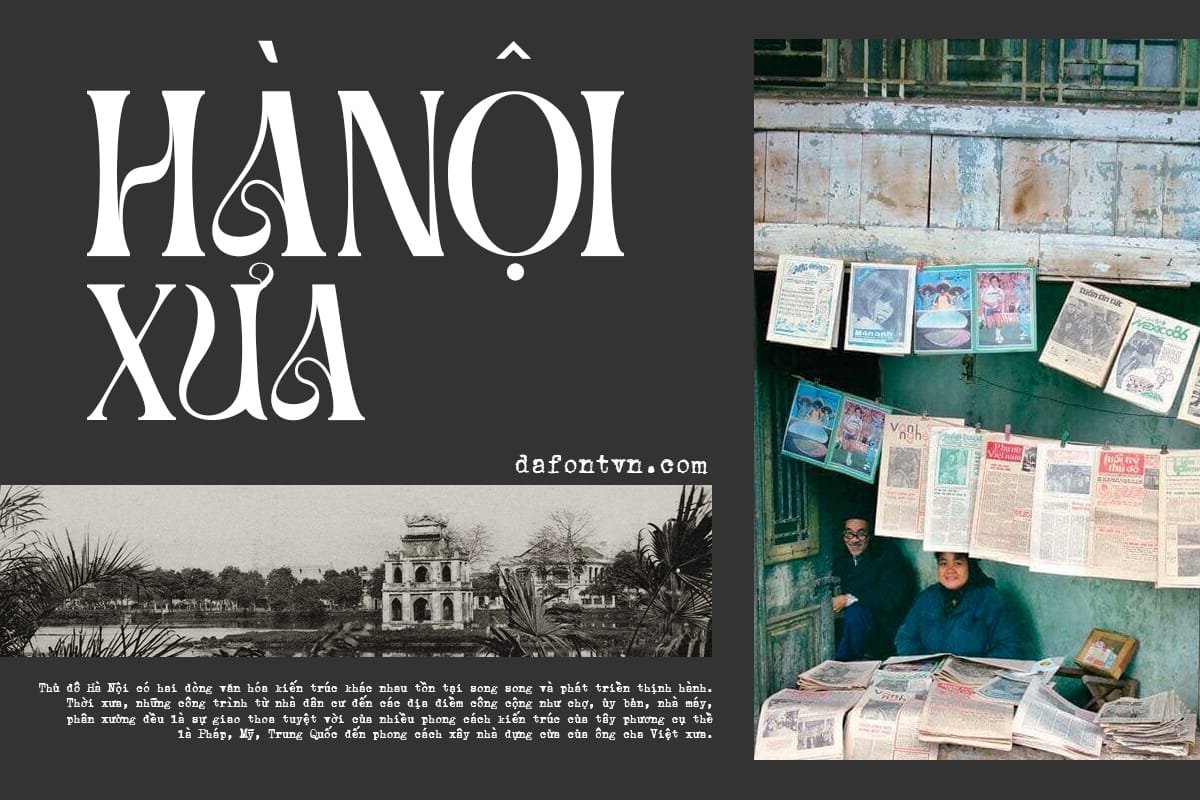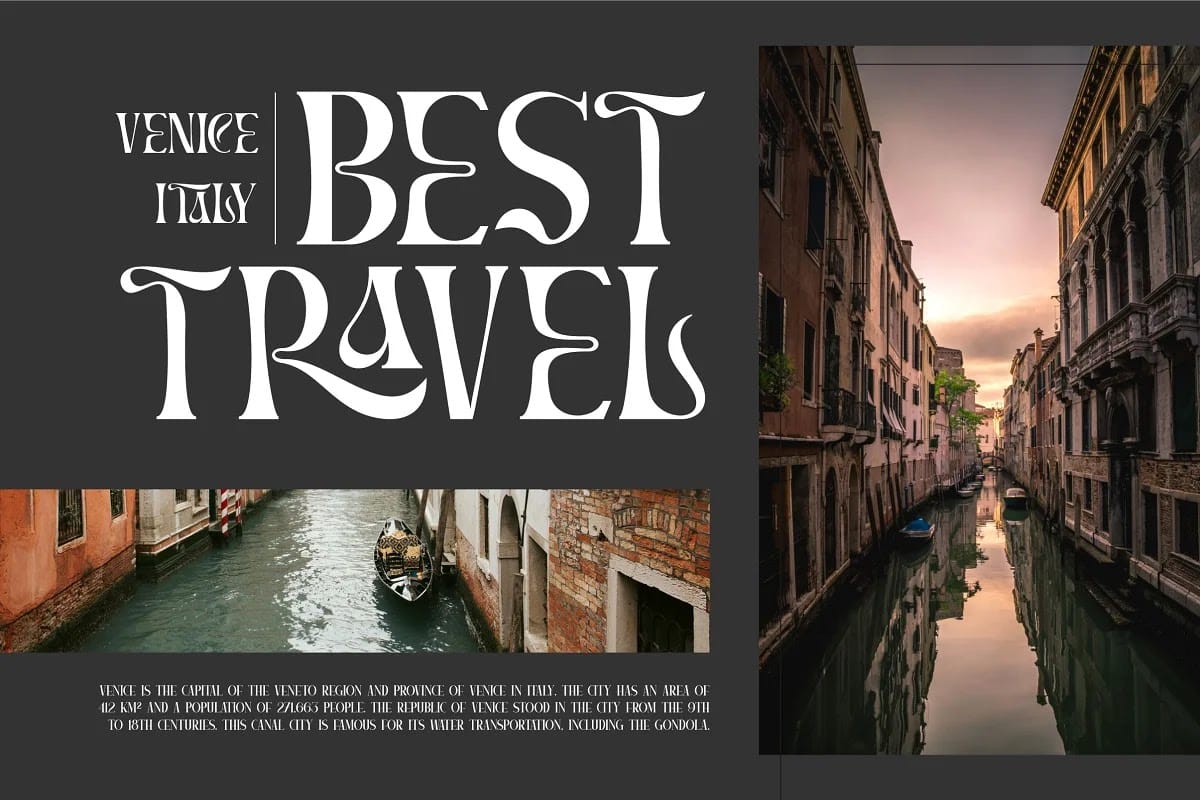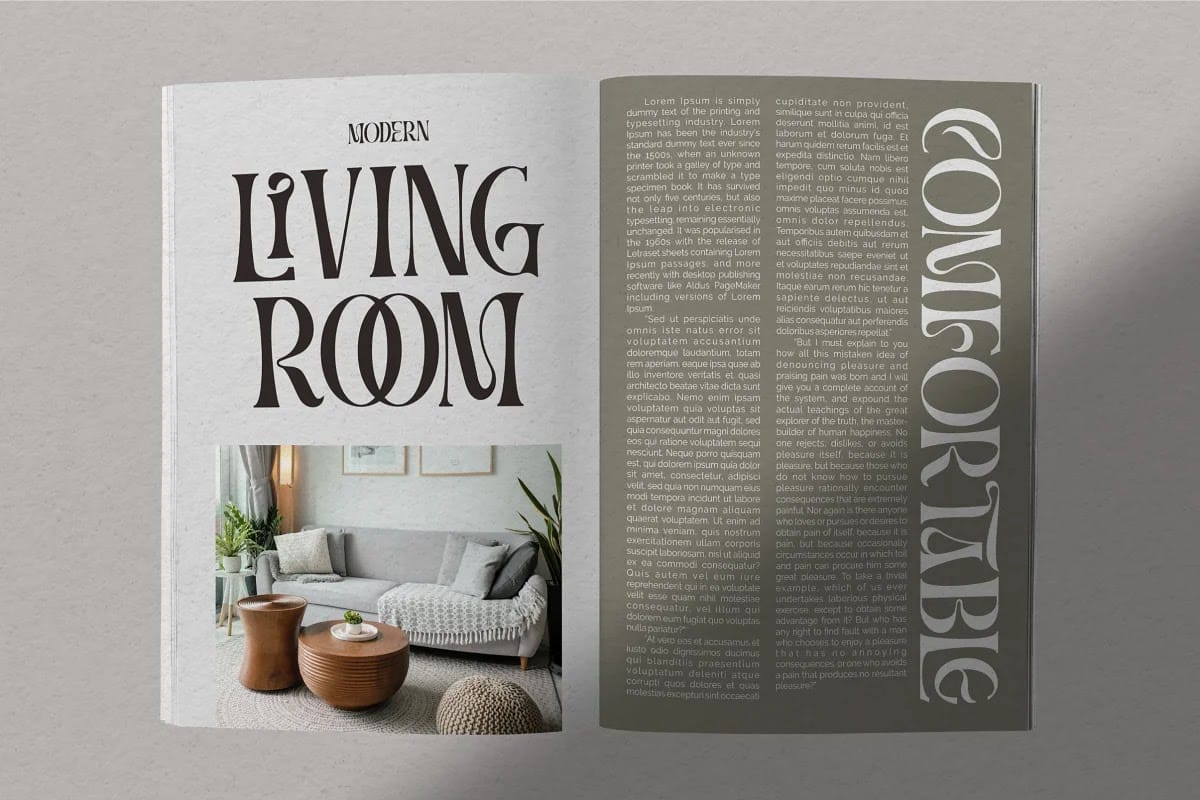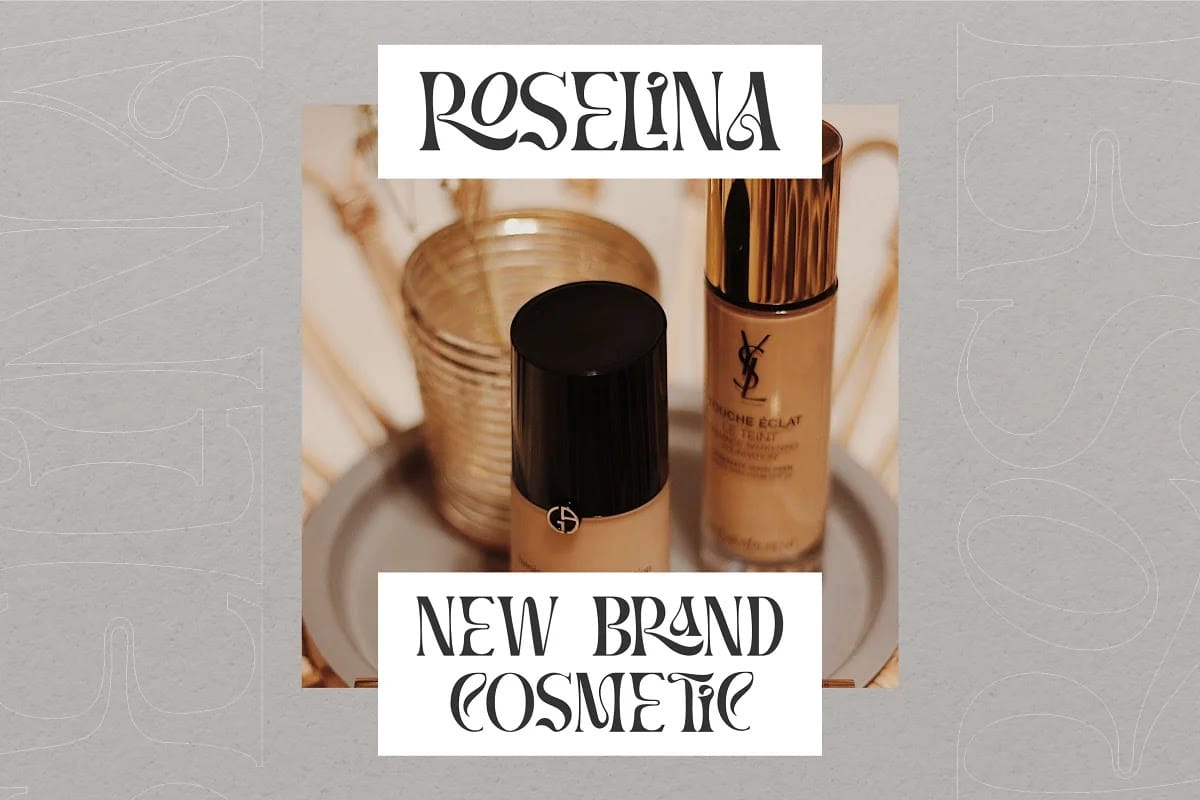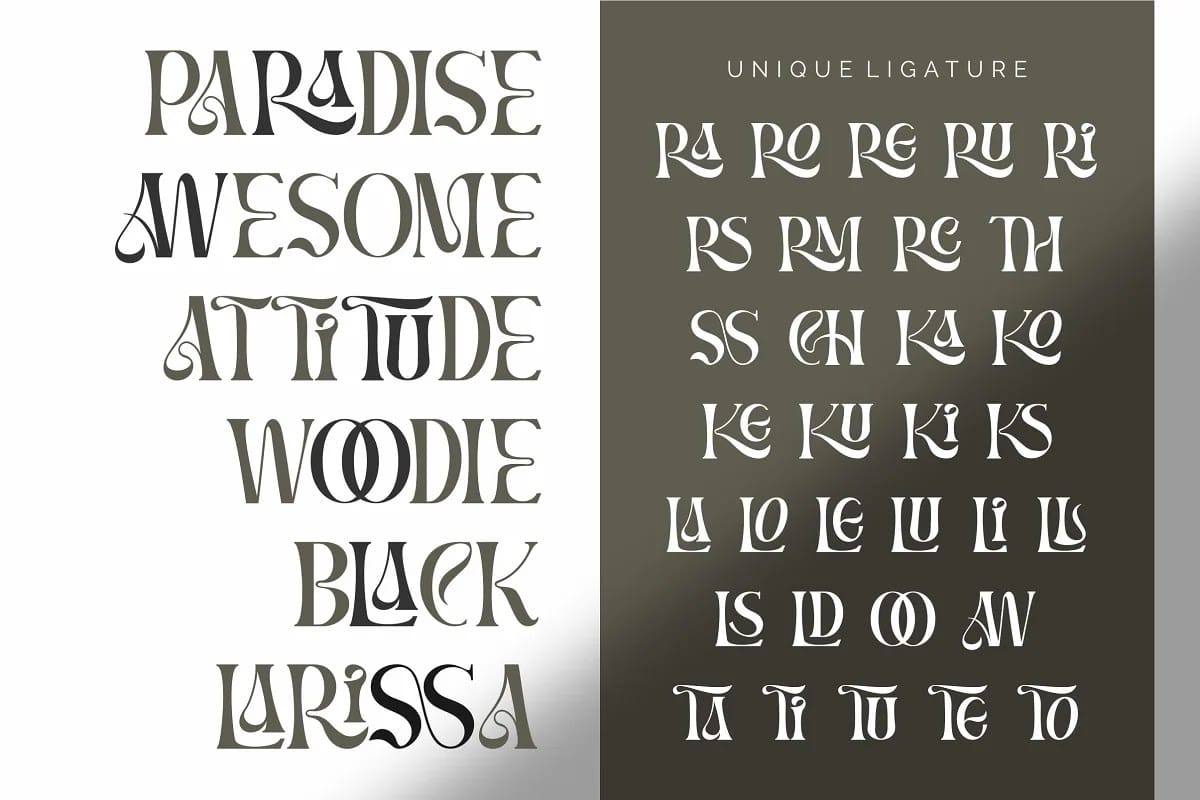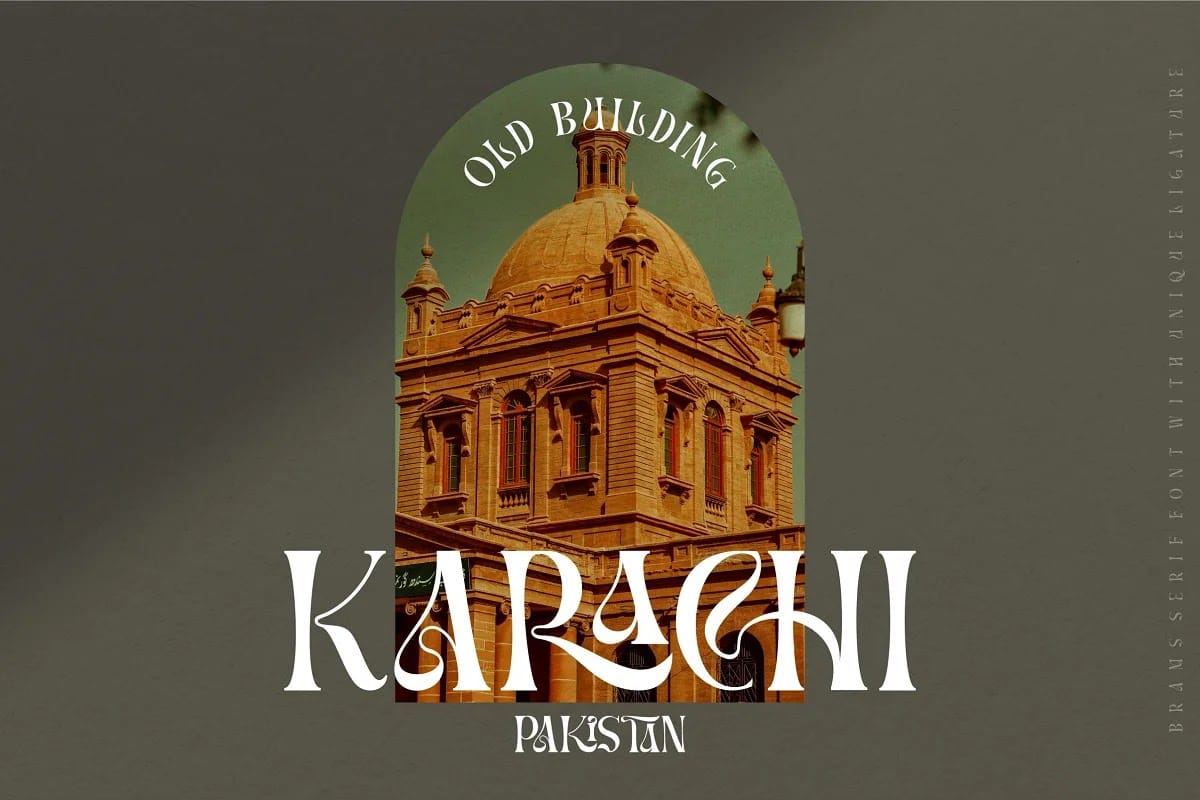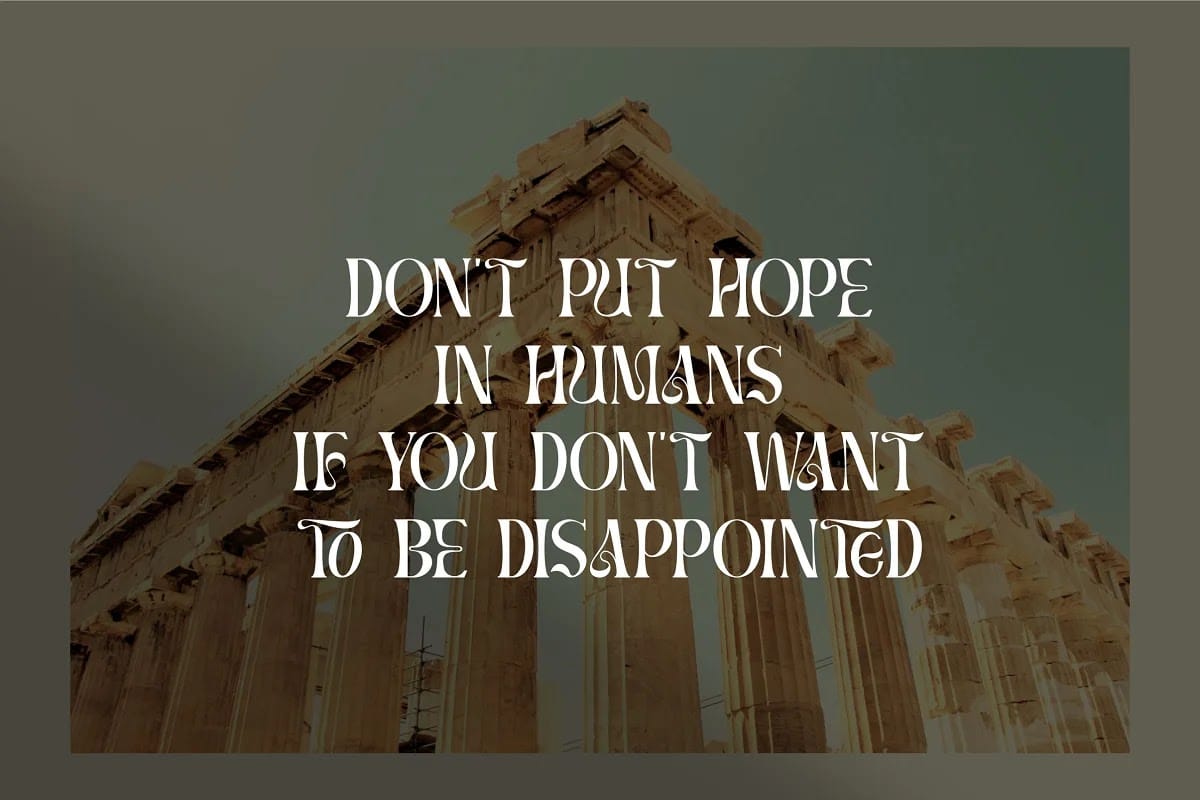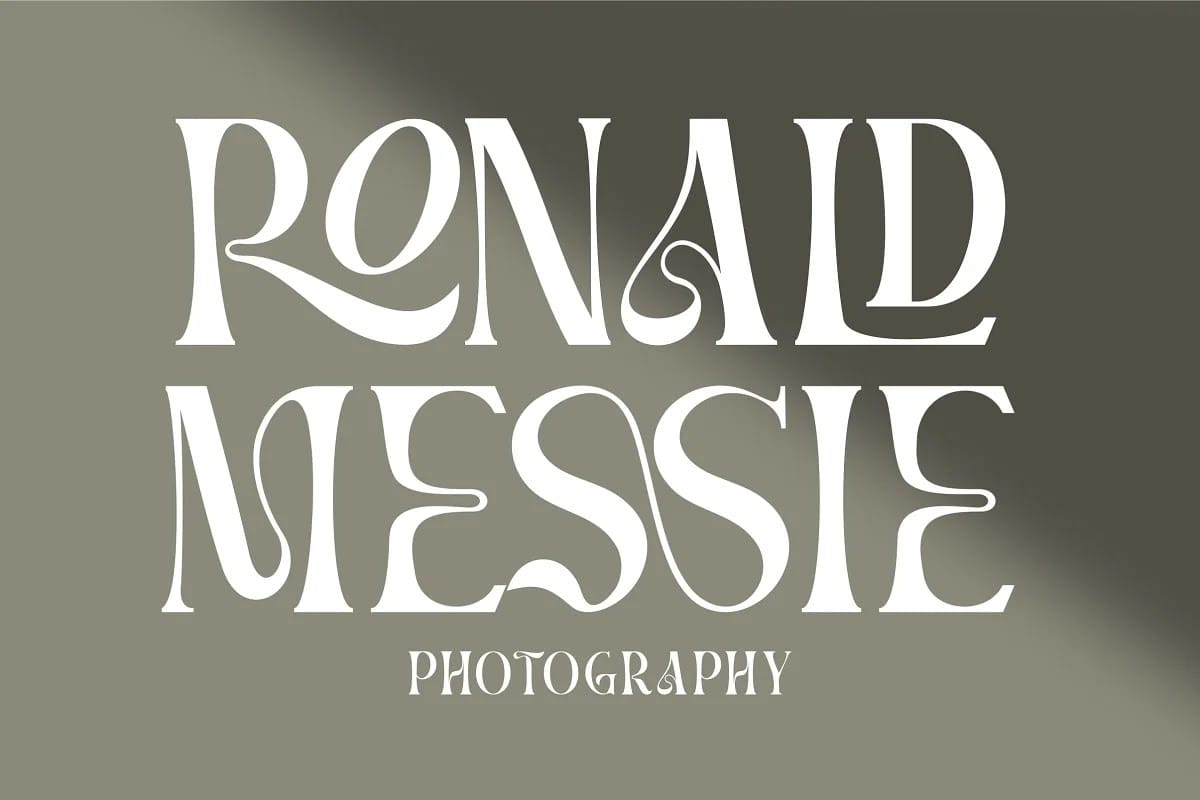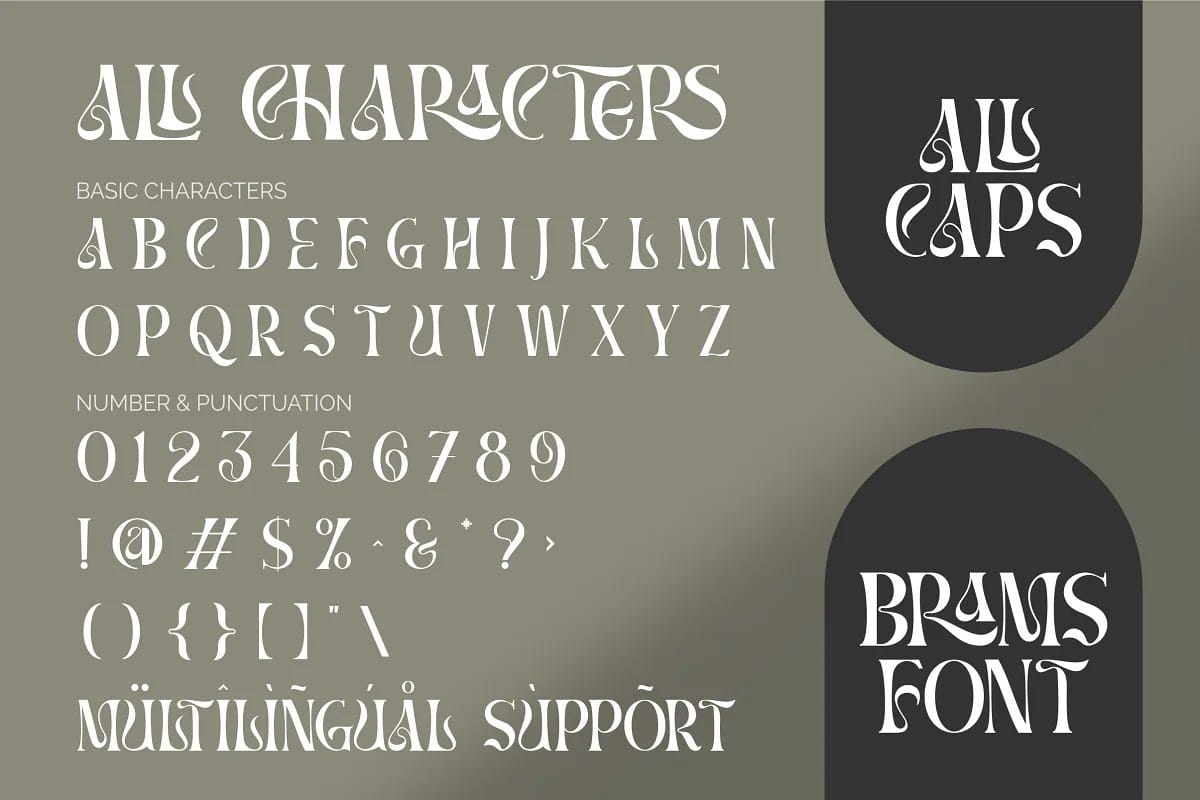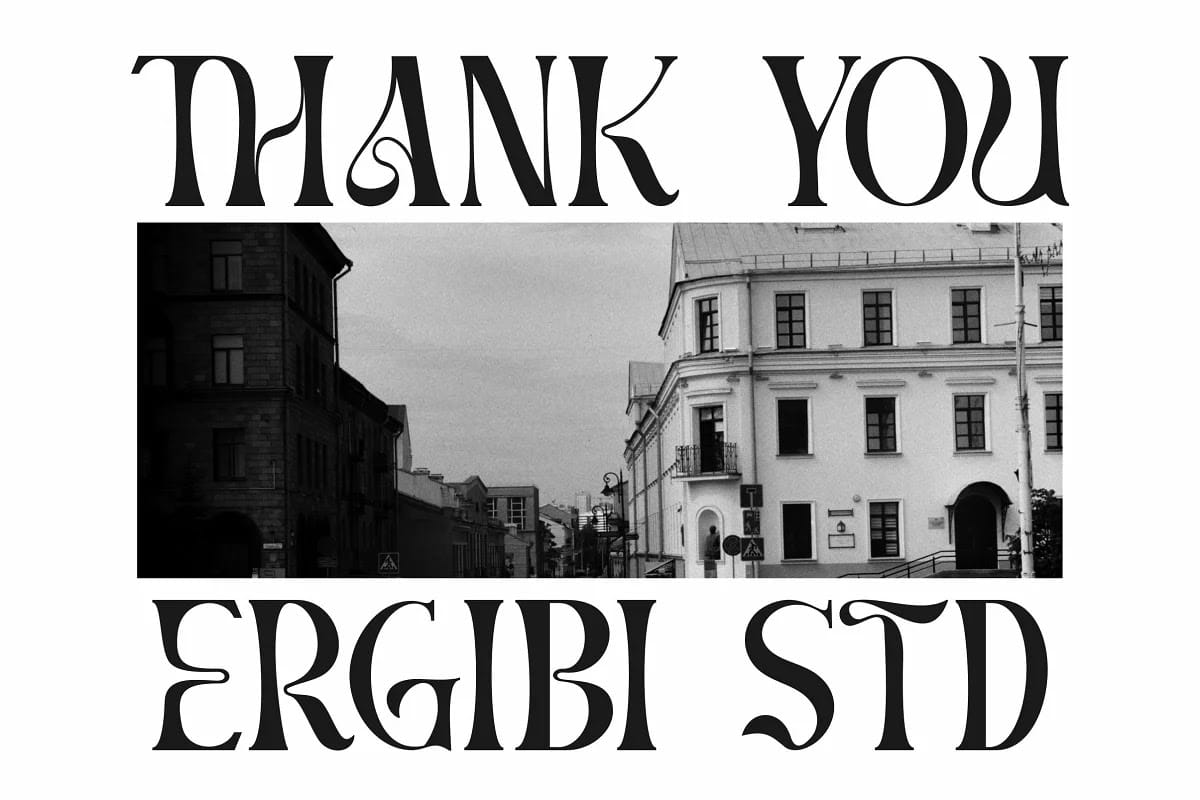
BRAMS Display Serif Font. Font chữ này có dạng chữ độc đáo và kiểu dáng đẹp, làm cho nó trở nên tuyệt vời để được sử dụng cho chủ đề thiết kế hiện đại và tối giản. Các chữ ghép độc đáo trên serif làm cho kiểu chữ này trở nên mát mẻ và nổi bật hơn là font serif thông thường, hoàn hảo cho các tiêu đề, biểu trưng, áp phích, bao bì, áo phông, quán cà phê… nhà hàng, tiêu đề tạp chí, bảng hiệu hoặc thẻ quà tặng / bưu điện, quán cà phê và đám cưới hoặc bất kỳ loại mục đích quảng cáo nào. BRAMS chỉ đi kèm với chữ hoa, chữ số, dấu câu, dấu gạch ngang và cũng hỗ trợ Đa ngôn ngữ.